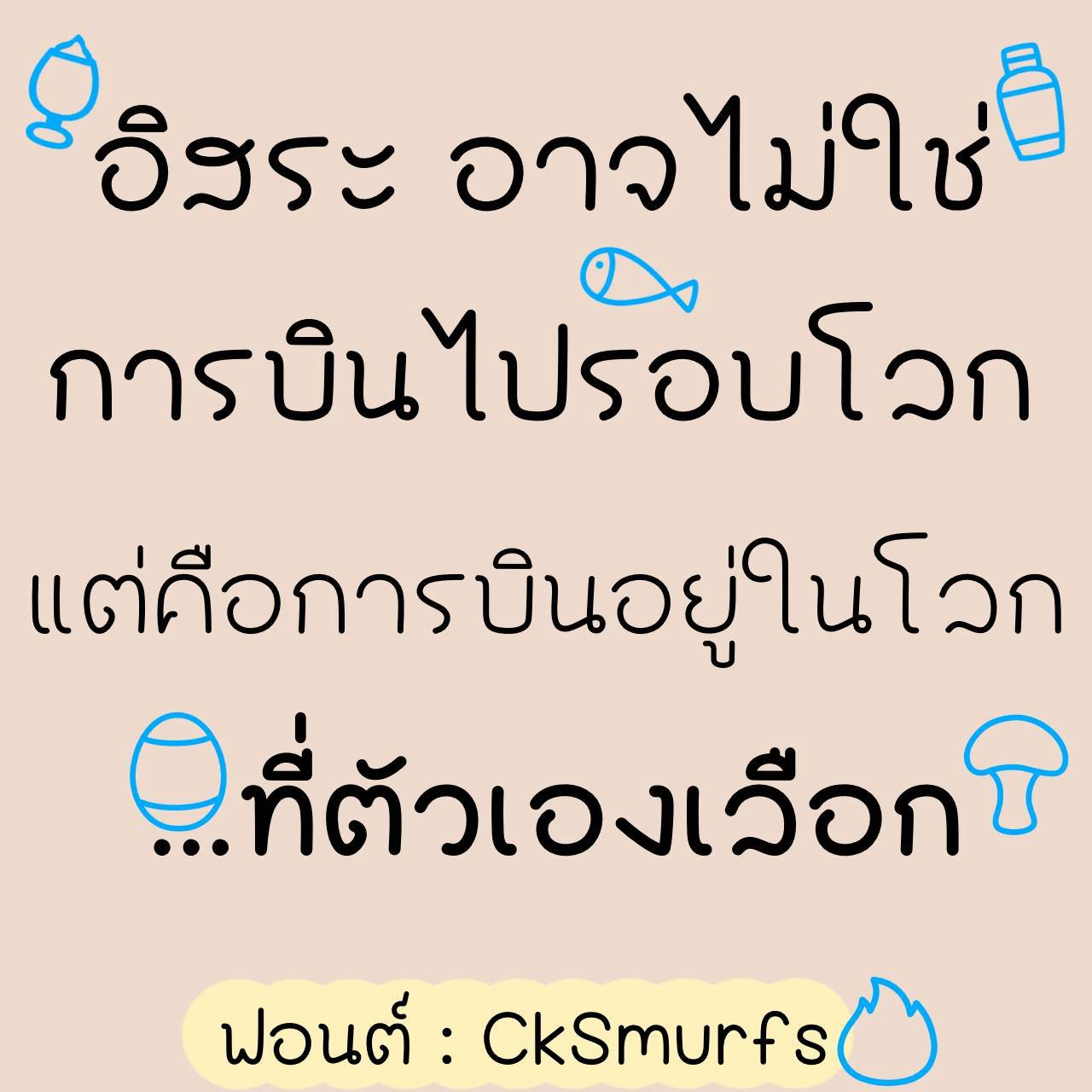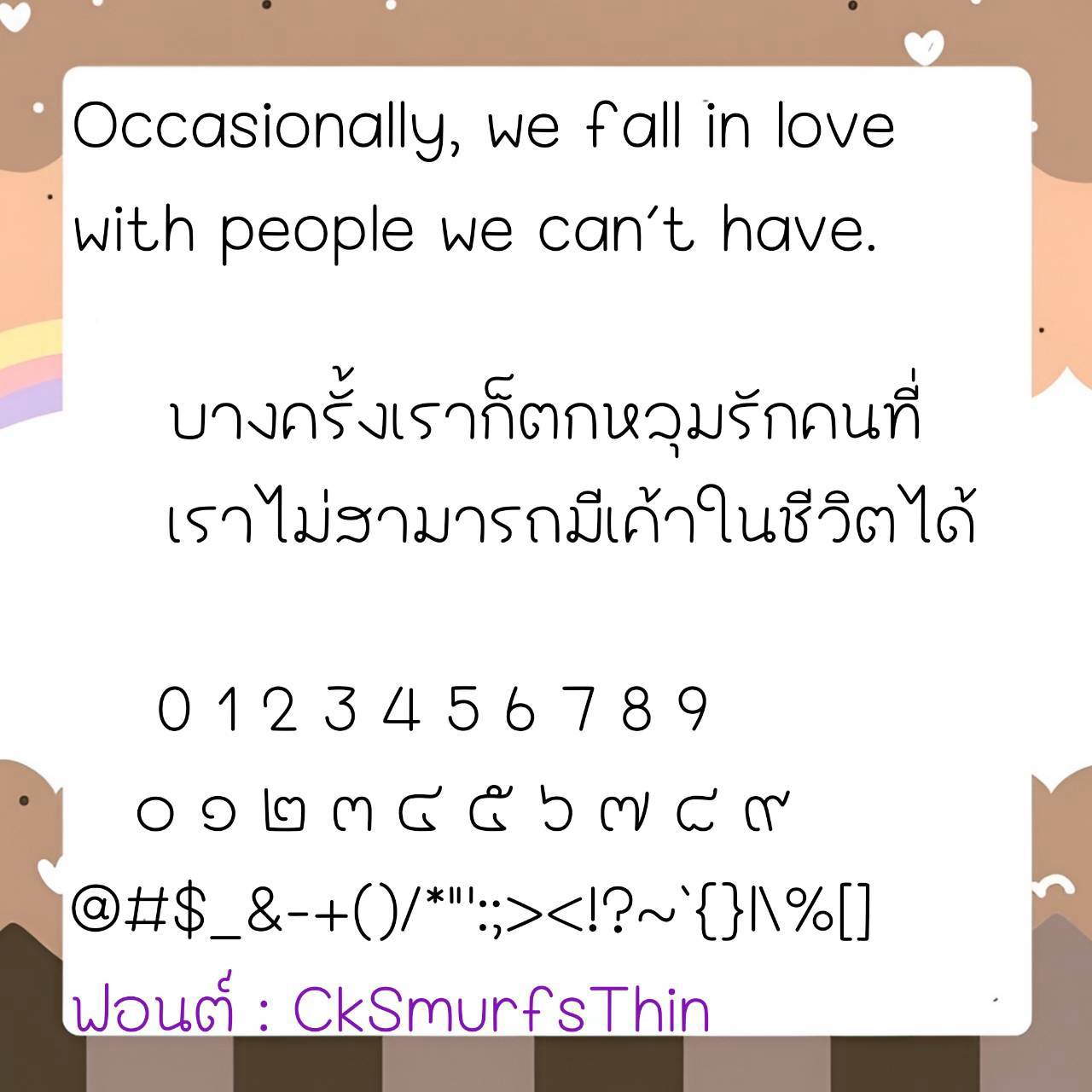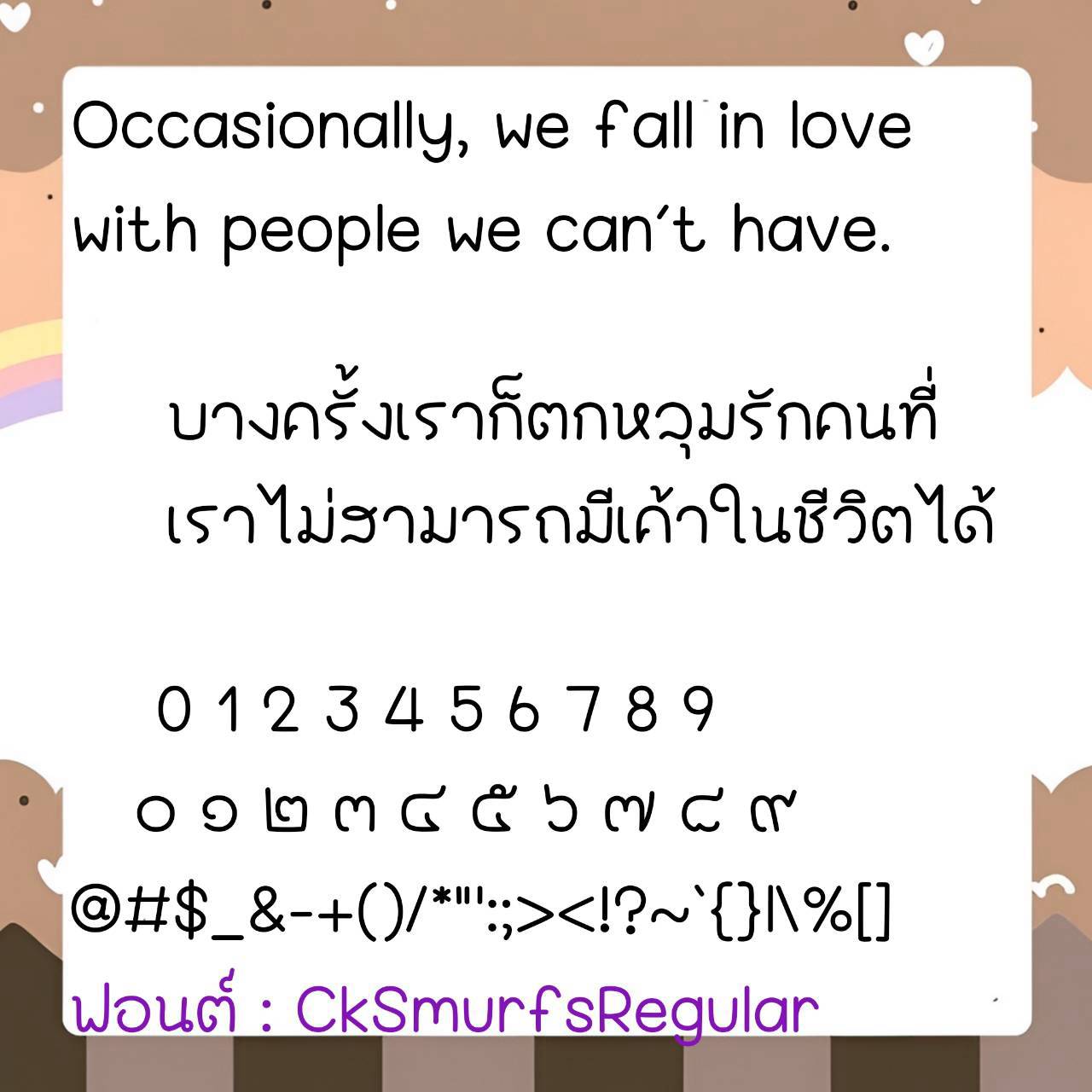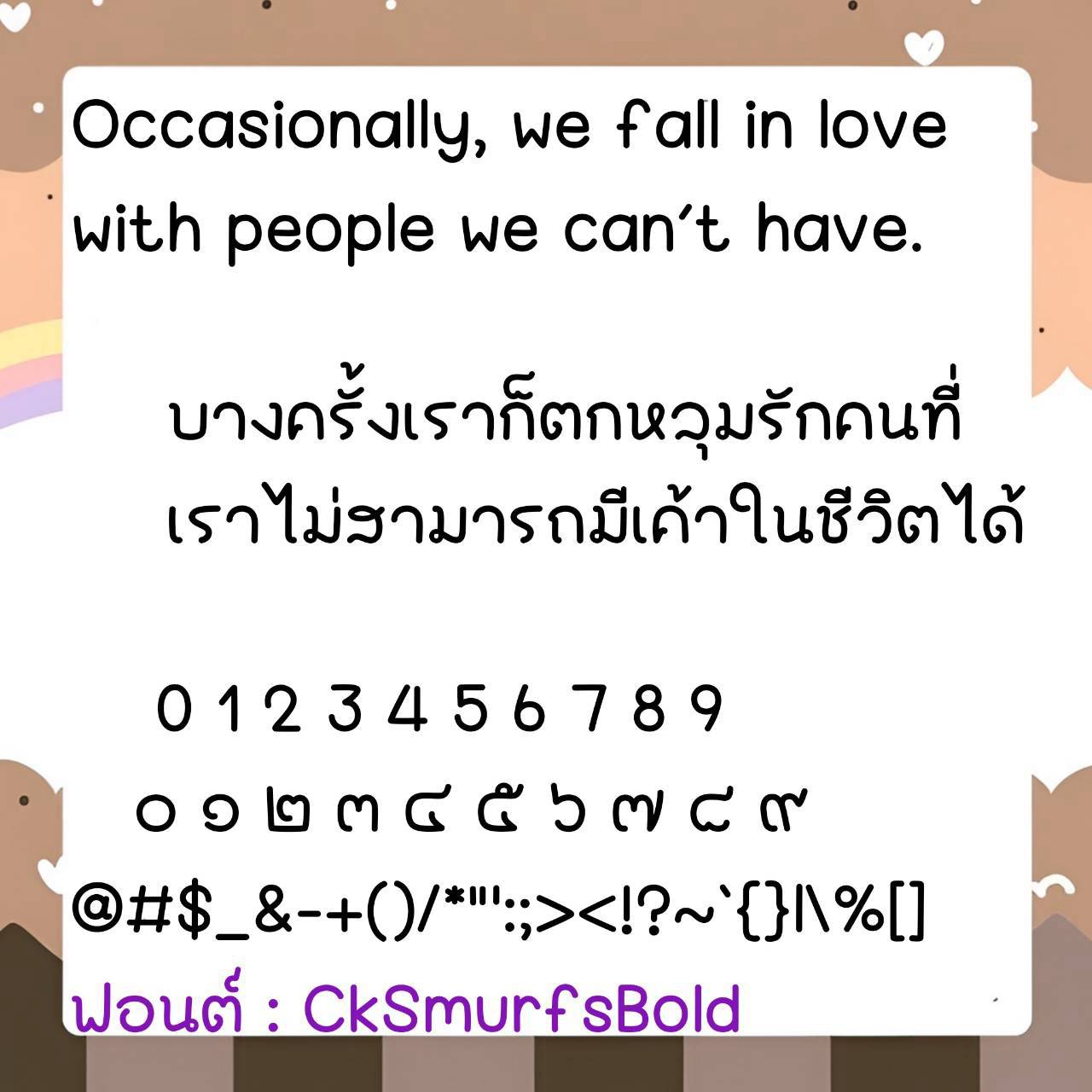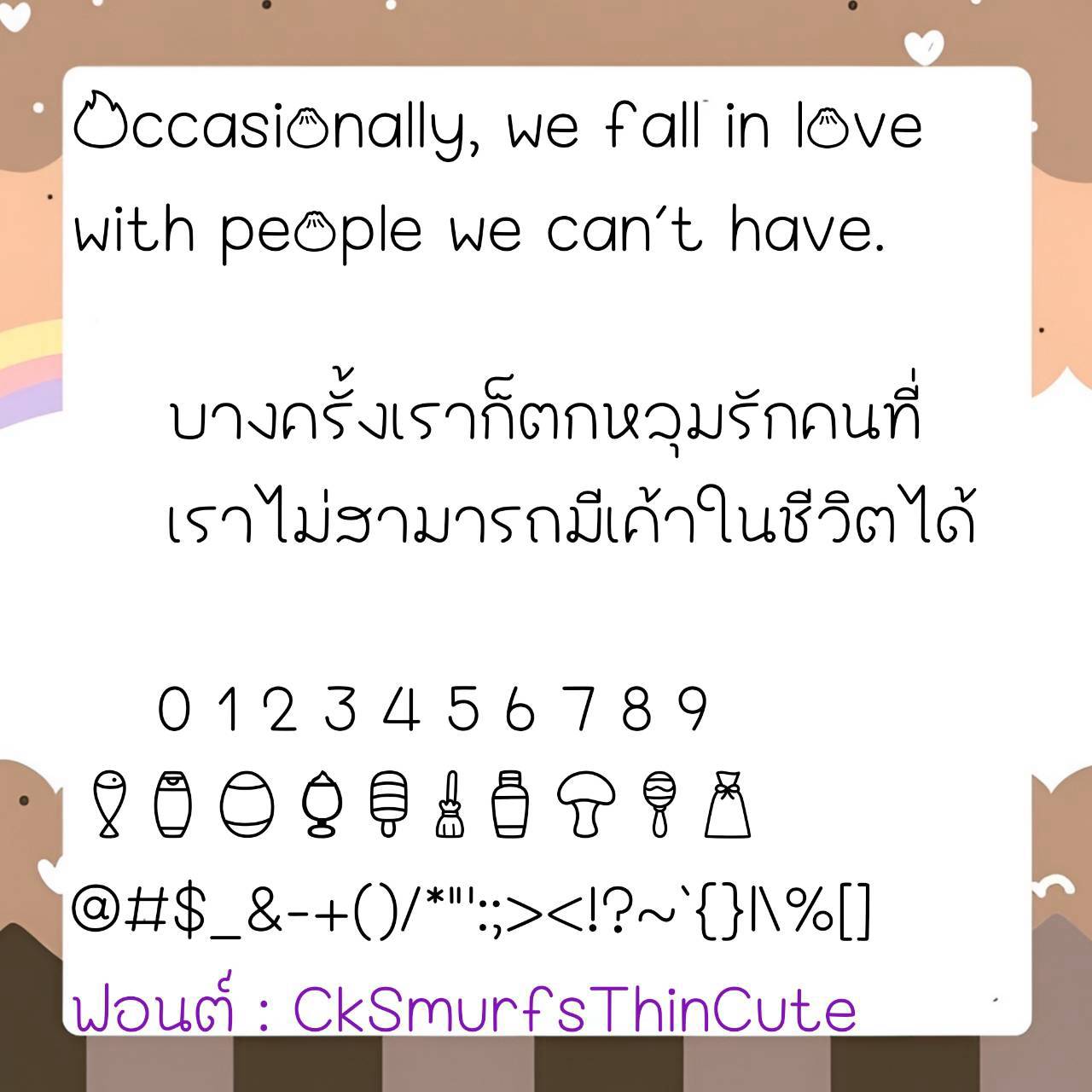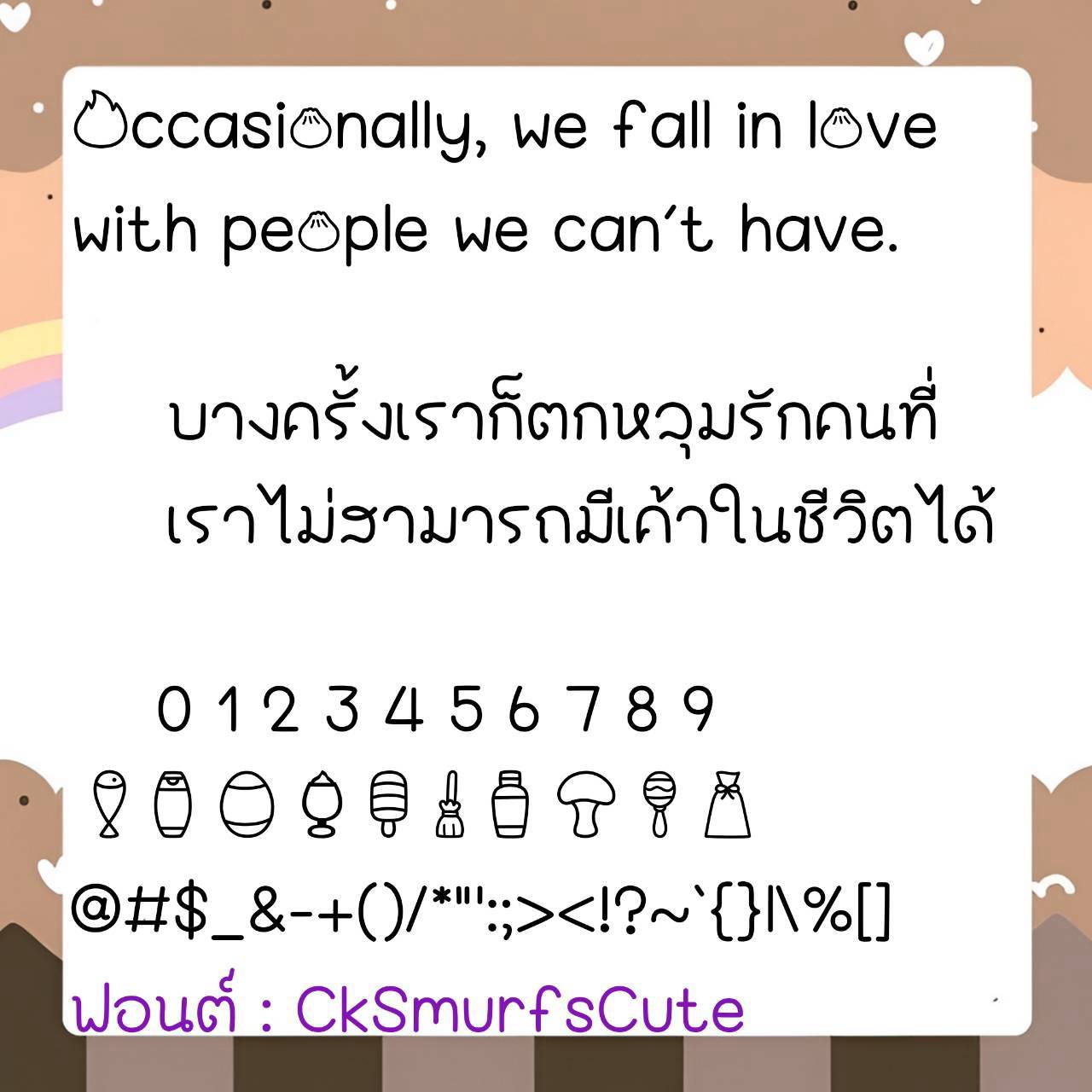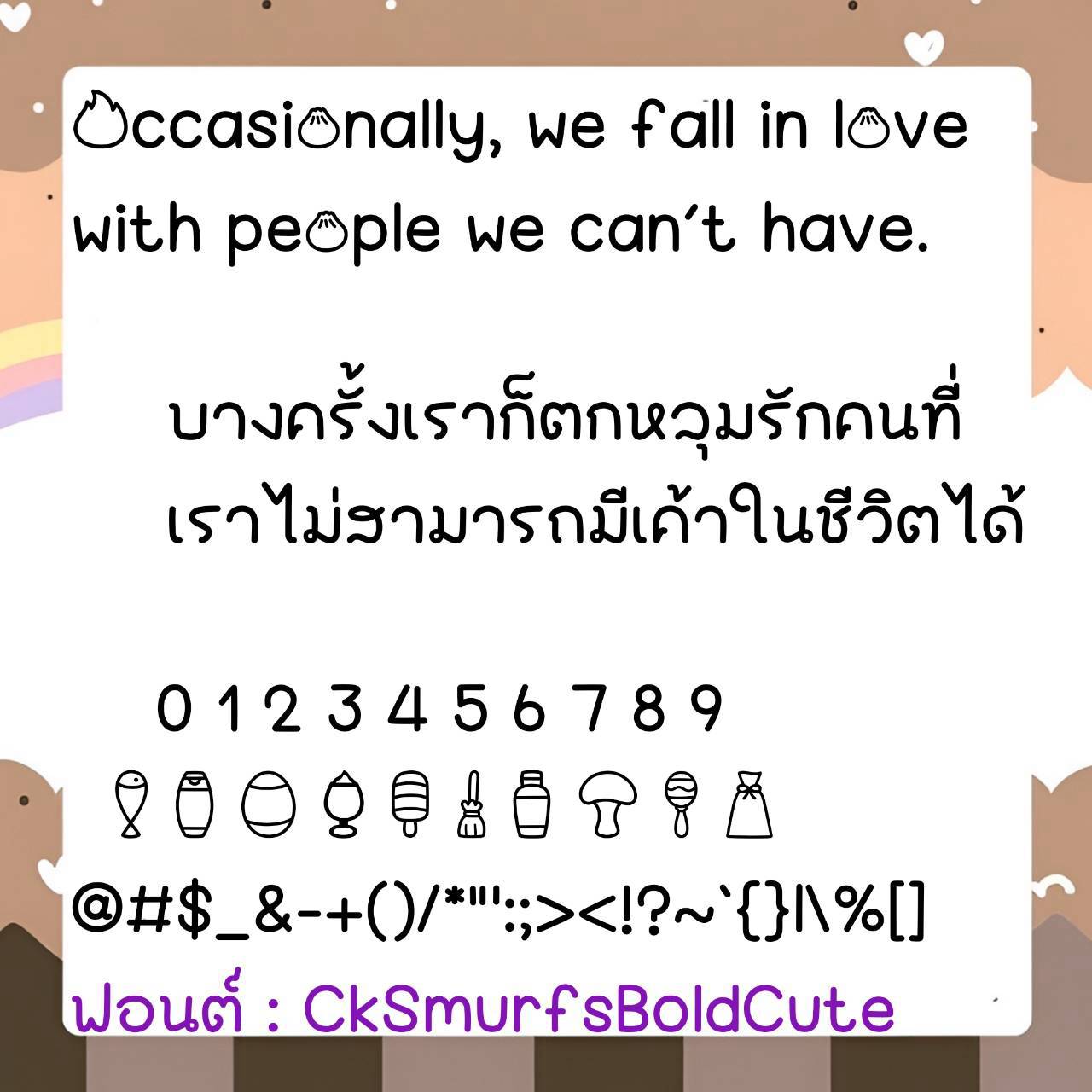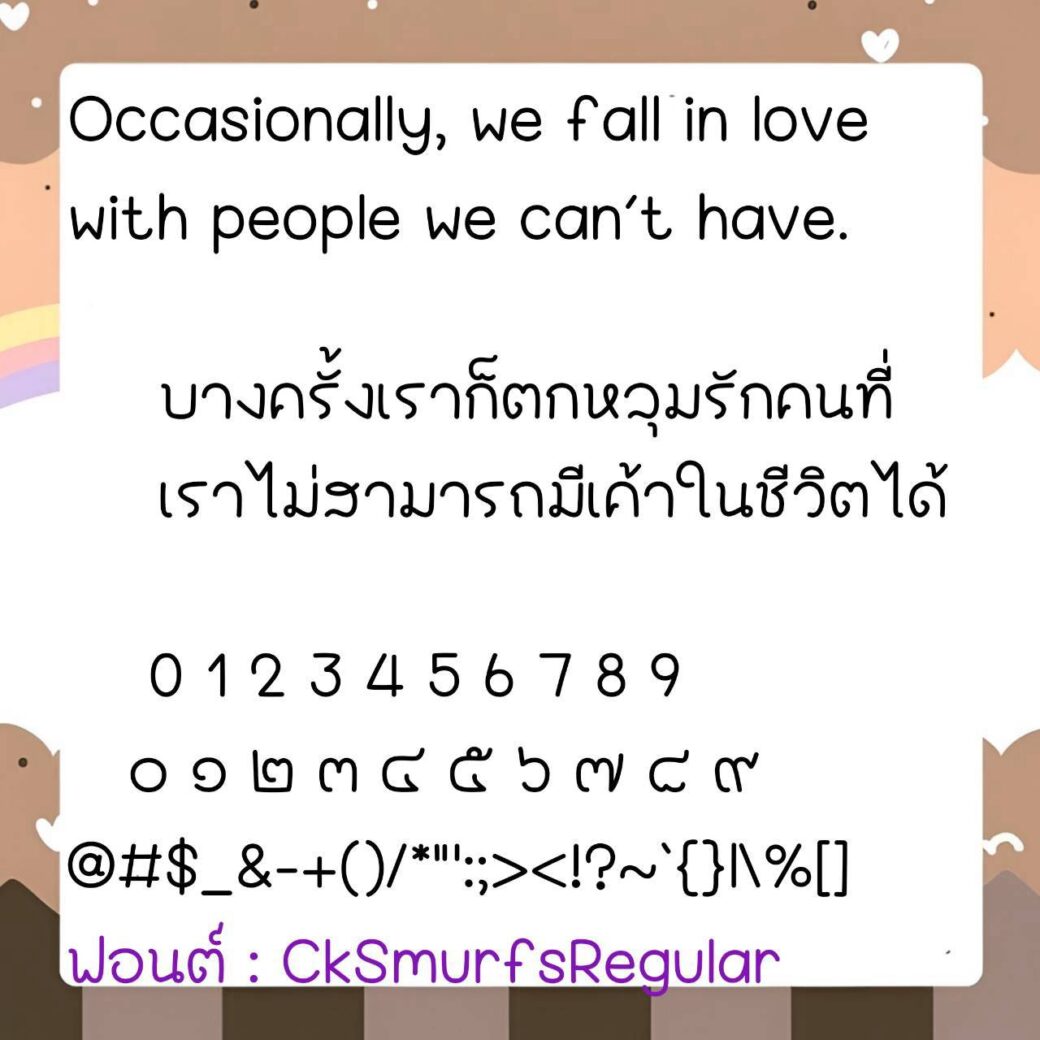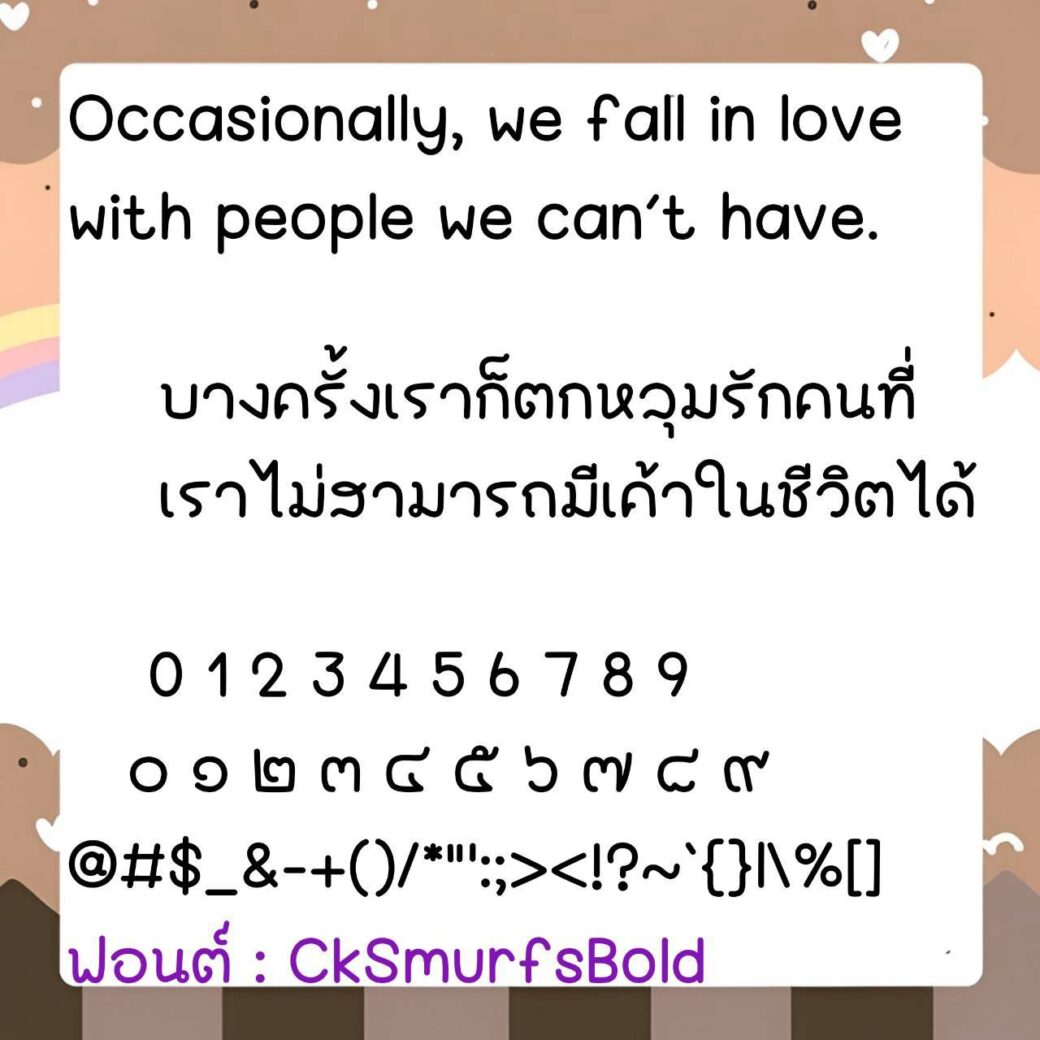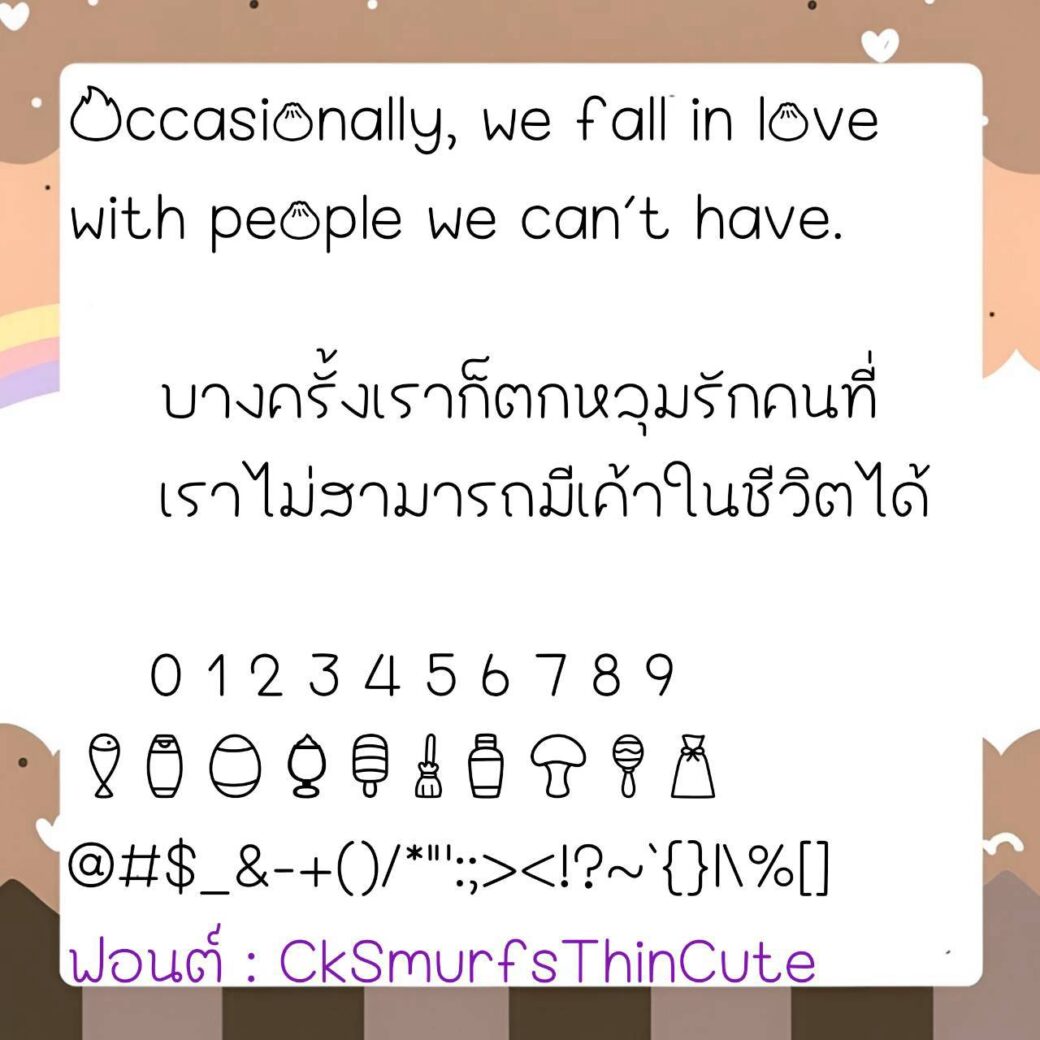
Font CkSmurfs
ชื่อสินค้า : Font CkSmurfs 💙
🔸 ฟอนต์ลายมือแนวไม่มีหัว ตัวอวบอ้วนน่ารัก คล้ายลายมือเขียนหวัดๆ แต่ยังอ่านง่าย และยังมีไฟล์อิโมจิน่ารักๆที่ใช้แทนเลขไทยให้ด้วยค่ะ 🥰💙
🔹 A cute, chubby, sans-serif handwritten font, similar to a messy handwriting but still easy to read. It also includes cute emoji files that can be used to represent Thai numerals. 🥰💙